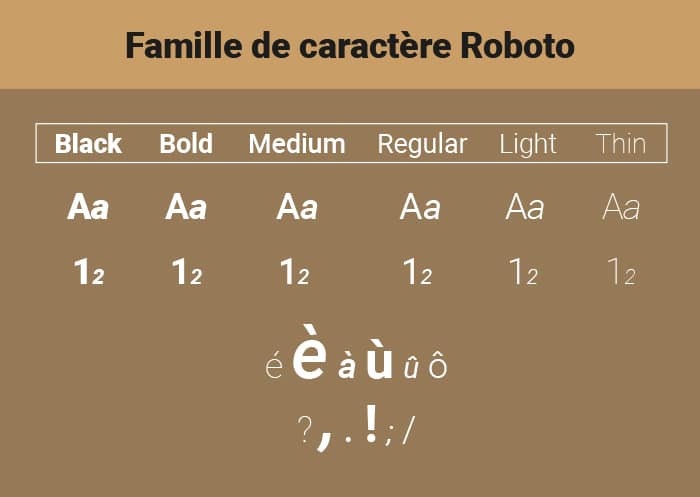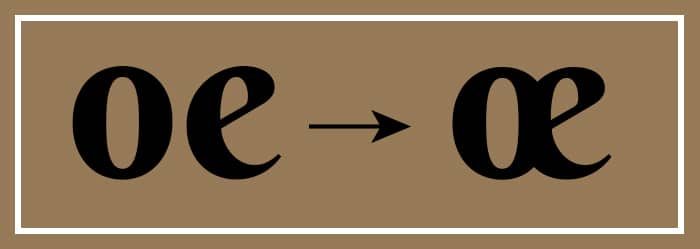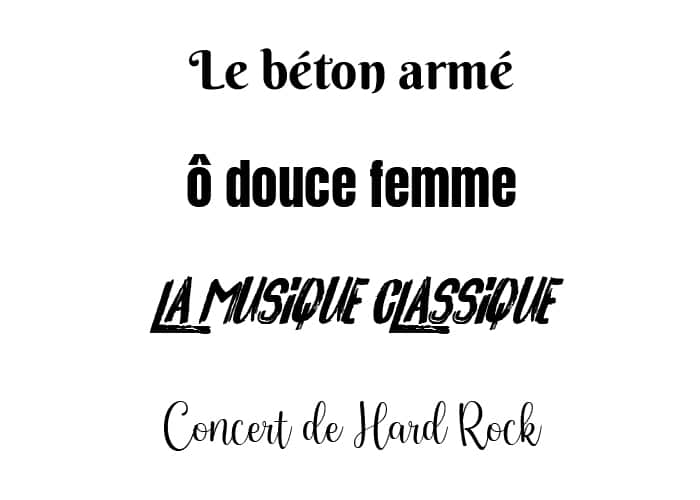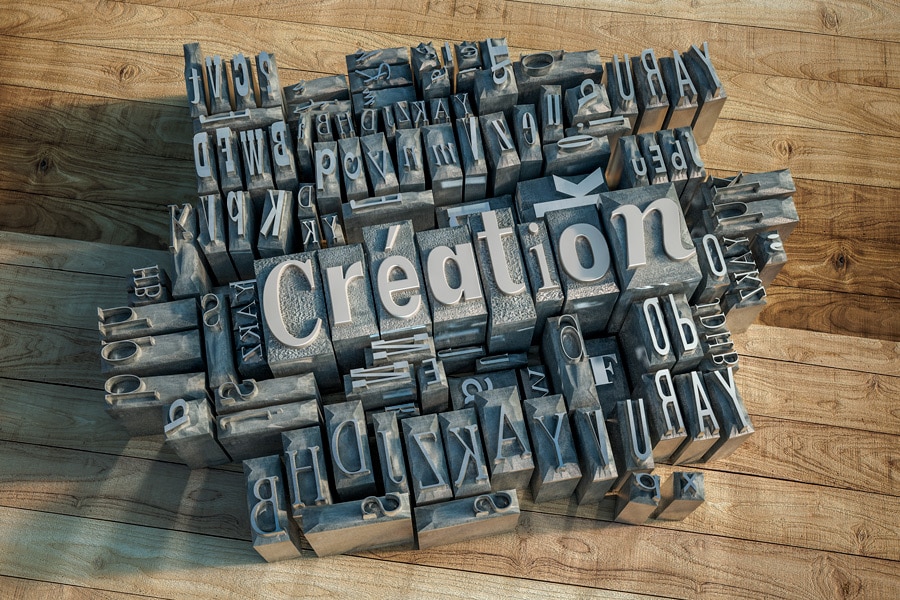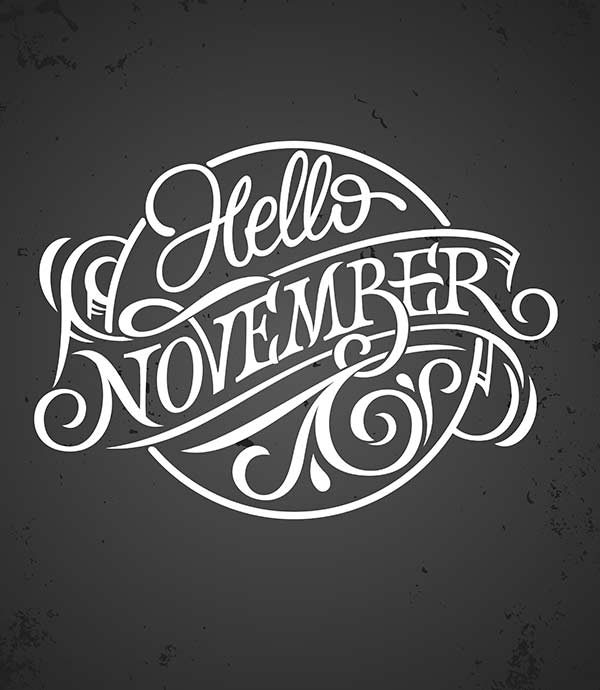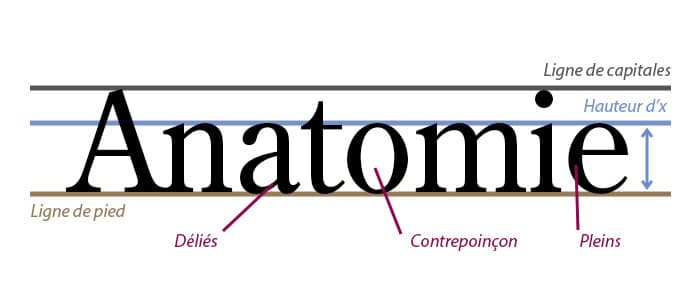
Qu’est-ce que la typographie ?
Notions sur les polices et caractères d’imprimerie
Saviez-vous que le mot anglais « font » pour « police d’écriture » – provient en réalité du mot français « fonte » ? C’est là une belle référence au petit caractère mobile en plomb, utilisé au 15 siècle avec l’avènement de l’imprimerie mécanique.
Cette anecdote fait partie du cortège de mots et de notions méconnus / mal compris, gravitant dans l’univers de la typographie. Il est temps de s’intéresser à cette discipline centrale dans les arts graphiques. Commençons par le vocabulaire pour bien préciser les choses…
Vocabulaire de la typographie et des caractères typographiques
Police de caractère, caractère typographique, famille de caractère, glyphes ou encore fonts : nous avons tous été confrontés à ces termes, sans trop pouvoir les définir précisément.
Bien que techniques au premier abord, ils deviennent aisément compréhensibles une fois expliqués et illustrés. Voici quelques définitions simples pour vous approprier le vocabulaire de la typographie.
La typographie : à l’origine, elle désigne l’art de créer et d’assembler des caractères pour composer des mots, des phrases et des feuillets. La typographie représente également la technique d’impression via des caractères mobiles en plomb, celle-là même qui fut mise au point par Johanes Gutenberg.
Les glyphes : le glyphe est un caractère typographique (ou un caractère d’imprimerie, en référence au caractère mobile en plomb sous Gutenberg). Il peut s’agir d’un caractère alphabétique, numérique ou encore d’un signe de ponctuation.
Certaines polices affichent même des glyphes supplémentaires, spécifiquement créés dans un but esthétique. C’est le cas de la ligature : elle permet la liaison élégante de 2 caractères, comme le fameux « e pris dans le o » du œ
Qu’est-ce qu’une police de caractère (ou font) ?
Une police se compose d’un ensemble de caractères ou glyphes ayant un design particulier. Dans le jeu de police, on trouve les lettres à proprement parler, les chiffres, les caractères spéciaux, la ponctuation et certaines variantes :
- la graisse (bold, thin) ;
- la forme ou le style (font-style) ;
- la taille (font-size) ;
- la casse (majuscule, minuscule).
Et une famille de caractère alors, quelle différence ?
Rigoureusement parlant, il existe une différence de fond entre police de caractère et famille de caractère (ou font-family) : Garamond 12pt bold et Garamond 14pt sont 2 polices de caractères différentes mais appartiennent toutes deux à la même famille de caractère, ici Garamond.
La personnalité des polices de caractère
Le dessin des lettres d’une police de caractère va influencer d’une part sa lisibilité, d’autre part l’identité, la personnalité qu’elle va être susceptible de véhiculer. Chaque caractère, par son dessin et ses attributs, peut dégager ou non une harmonie avec l’esprit du texte.
On cite bien souvent des exemples de ce genre, manifestement à côté du sujet :
Le choix de la typographie doit donc se faire en accord avec le message textuel afin de ne pas créer de dissonance entre le fond et la forme.
Avant même la lecture du contenu, la typographie apporte une charge émotionnelle et une atmosphère particulière au design. Une typographie bien choisie et cohérente avec la ligne graphique de la composition retient l’attention du lecteur et le plonge dans un univers particulier. Le style peut être formel, décontracté, convivial, moderne…
Anatomie de la lettre et des caractères typographiques :
Très souvent, choisir une typographie » stylée » est une question de détail. « La hampe des « l » ou des « t » est particulièrement originale », « ces déliés-là sont fins et élégants », ou encore : « l’absence d’empattements convient bien pour cette création web », etc.
L’anatomie des caractères est analysée à la loupe pour dénicher ce petit plus qui fera toute la différence… Connaître le vocabulaire anatomique des caractères typographiques sera alors d’une grande aide pour argumenter et expliquer son choix de police.
Cette image a été créée par Alcandre pour l’article Caractère (typographie) de Wikipédia.
La ligne de base ou ligne de pied assoit la typographie. Tous les caractères sont alignés sur elle, même si certains la dépassent.
La hauteur d’x est, comme son nom l’indique, la hauteur de la lettre « x » : elle est devenue la référence pour définir la hauteur de toutes les minuscules (en exceptant leurs jambages). Pourquoi le « x » ? Dans la plupart des polices, le x garde une hauteur constante alors que les a, les o – plus arrondis – peuvent avoir tendance à dépasser cette ligne médiane, pour une question d’équilibre optique.
La ligne de capitale désigne la hauteur atteinte par les capitales, mais aussi par les minuscules à jambage ascendant, comme l, t, h. Notez que le jambage ascendant est la partie du fût ou de la hampe dépassant la hauteur d’x.
A contrario, la ligne descendante désigne le point le plus bas, atteint par les lettres y, j, p par exemple, à jambage descendant (partie de la hampe sous la ligne de base)
Le contrepoinçon est un espace blanc clos, tout ou partie, à l’intérieur d’un caractère. L’exemple le plus probant est certainement le « o »
Les Pleins et déliés se retrouvent dans certaines polices historiques, un même caractère peut afficher une partie épaisse (le plein) et une partie plus fine (le délié).
Police avec ou sans empattement (Serif)?
Les Empattements sont une autre des caractéristiques des polices historiques dites « Serif ». L’empattement est un trait horizontal ou une terminaison triangulaire, venant finir le pied ou la tête d’un jambage.
Les caractères sans empattements, eux, sont apparus début XIXème pour les besoins de la publicité naissante. Ils ont la propriété de pouvoir supporter des graisses importantes (d’où leur bonne visibilité de loin) et de pouvoir être fortement étroitisés et serrés les uns contre les autres : l’absence d’empattements permet un véritable gain de place !
- Les polices sans Serif sont idéales pour les titres et les petits tirages, tant leur visuel est percutant.
- Elles sont aussi recommandées pour le Web : leur affichage nécessite un nombre moins important de pixels.
- Par contre, leur aspect uniforme peut rendre la lecture délicate, du fait du peu de distinction dans l’affichage des caractères.
Les caractères avec empattements sont conseillés pour les longs écrits papier, leur lecture est plus reposante pour l’œil : à y regarder de plus près, leurs empattements forment comme de petits rails qui permettent une lecture linéaire plus efficace.
Le crénage, un réglage optique
Pour que le texte se lise sans peine, l’espacement entre les lettres doit être visuellement correct. La technique d’ajustement est appelée crénage : elle consiste à diminuer ou augmenter l’espace entre certaines paires de lettres. Le crénage est particulièrement utile sur les caractères de plus grande taille, comme les titres : sans lui, les écarts paraîtraient disgracieux :
- WIK
- WAK (3 lettres mais WAK prend plus de place)